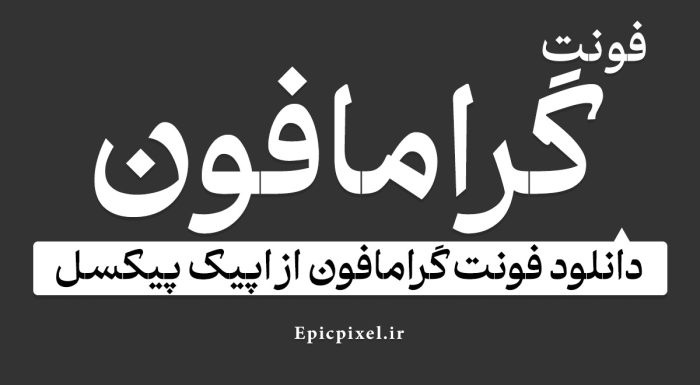
| ⭐ مجموعه فونت | دانلود فونت فارسی گرامافون سه بعدی Font Epic Gramophone 3D فونت گراموفون تمیز Epic Gramophone Clean اپیک گرامافونت حکاکی Epic Gramophone Engrave دانلود فونت اپیک گرامافون گرانج Epic Gramophone Grunge اپیک گرامافون دور خط Epic Gramophone Outline گرامافون نرم Epic Gramophone Smooth فونت گراموفون فارسی سنگی Epic Gramophone Stone |
| ⭐ توضیحات | مجموعه ای کامل از فونت های گرامافون و نسخه شبیه سازی شده اپیک گرامافون فونت اپیک گرامافون با پشتیبانی از حروف فارسی و انگلیسی ، اعداد فارسی Fu Num بهمراه نسخه وب دارای 7 سبک مختلف که در بالا لیست شدهدانلود فونت گرامافون، یک فونت نوستالژیک و زیبا با الهام از خطوط نسخ قدیمی است. این فونت حس اصالت و زیبایی را به طرحهای شما میبخشد و برای طیف وسیعی از پروژهها مانند طراحی جلد کتاب، پوستر، لوگو، و تیتر مناسب است. |
فونت گرامافون نوستالژی و زیبایی در یک قلم
در دنیای طراحی گرافیکی و به ویژه تایپوگرافی، فونتهای مختلفی وجود دارند که هر یک ویژگیها و کاربردهای خاص خود را دارند. یکی از این فونتهای زیبا و منحصربهفرد، فونت گرامافون است که در سال 1399 طراحی و عرضه شد. این فونت به دلیل شباهت ظاهری آن با خطوط نسخ قدیمی، حس نوستالژی و اصالت را به بیننده القا میکند و در عین حال، زیبایی و ظرافت خطوط نسخ را نیز به خوبی حفظ کرده است.
فونت گرامافون بازگو کننده زیبایی خطوط نسخ
الهام گرفتن از خطوط نسخ قدیمی
طراحی فونت گرامافون برگرفته از خطوط نسخ قدیمی و کتابهای خطی فارسی است که در گذشته برای کتابت متون مختلف استفاده میشدند. این خطوط به دلیل زیبایی، ظرافت و خوانایی بالای خود، همواره مورد توجه هنرمندان و خوشنویسان ایرانی بودهاند.
ویژگیهای فونت گرامافون
فونت گرامافون دارای ویژگیهای منحصربهفردی است که آن را از سایر فونتهای نسخ متمایز میکند. این ویژگیها عبارتند از:
ساختار حروف پیوسته: حروف در این فونت به صورت متصل طراحی شدهاند که باعث ایجاد حس پیوستگی و یکپارچگی در متن میشود.
ضخامت و تنوع: فونت گرامافون در 7 سبک مختلف ارائه شده است که هر یک ویژگیهای بصری خاص خود را دارند.
خوانایی بالا: فونت گرامافون در عین زیبایی، دارای خوانایی بالایی است و به راحتی قابل خواندن است.
قابلیت استفاده در انواع پروژهها: این فونت را میتوان در طیف وسیعی از پروژههای طراحی گرافیکی، از جمله طراحی پوستر، جلد کتاب و طراحی وب سایت، استفاده کرد.
کاربرد فونت گرامافون
فونت گرامافون به دلیل ویژگیهای منحصربهفرد خود، کاربردهای مختلفی دارد. این فونت به ویژه برای پروژههایی که به دنبال ایجاد حس نوستالژی، اصالت و زیبایی هستند، مناسب است. برخی از کاربردهای این فونت عبارتند از:
طراحی پوسترهای تبلیغاتی با مضمون سنتی یا نوستالژیک
طراحی جلد کتابهای قدیمی و تاریخی
طراحی وب سایتهای با تم سنتی یا نوستالژیک
طراحی استوریهای اینستاگرام و سایر شبکههای اجتماعی
طراحی صفحات تبلیغاتی در روزنامهها و مجلات
فونت گرامافون یک فونت زیبا و منحصربهفرد است که میتواند زیبایی و اصالت خطوط نسخ قدیمی را به پروژههای شما منتقل کند. این فونت به دلیل خوانایی بالای خود، برای طیف وسیعی از پروژههای طراحی گرافیکی مناسب است. اگر به دنبال ایجاد حس نوستالژی، اصالت و زیبایی در پروژههای خود هستید، حتماً فونت گرامافون را امتحان کنید.
آیا فونت گرامافون دارای نسخههای مختلف است؟
بله، فونت گرامافون در هفت سبک مختلف ارائه شده است که هر یک ویژگیهای بصری خاص خود را دارند.
Clean: این سبک سادهترین و خواناترین سبک فونت گرامافون است.
Grunge: این سبک دارای بافت و خطوط خشن است که حس نوستالژی و اصالت را بیشتر میکند.
Stone: این سبک دارای خطوط ضخیم و محکم است که حس قدرت و استحکام را القا میکند.
Engrave: این سبک دارای خطوط داخل فونت میباشد
3D: این سبک فونت گرامافون به سبک سه بعدی و سایه دار میباشد
Outline: سبک توخالی از فونت با خطوط دور
Smooth: سبک گوشه گرد فونت گرامافون
بله، فونت گرامافون برای استفاده در کتابهای چاپی نیز مناسب است. این فونت دارای خوانایی بالایی است و میتواند برای عناوین، زیرنویسها و متنهای طولانی استفاده شود.
فونت گرامافون یک فونت زیبا و منحصربهفرد است که میتواند زیبایی و اصالت خطوط نسخ قدیمی را به پروژههای شما منتقل کند. این فونت به دلیل خوانایی بالای خود، برای طیف وسیعی از پروژههای طراحی گرافیکی مناسب است. اگر به دنبال ایجاد حس نوستالژی، اصالت و زیبایی در پروژههای خود هستید، حتماً فونت گرامافون را امتحان کنید.